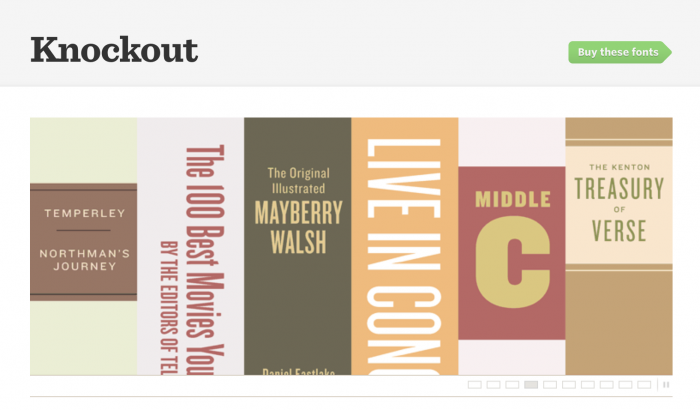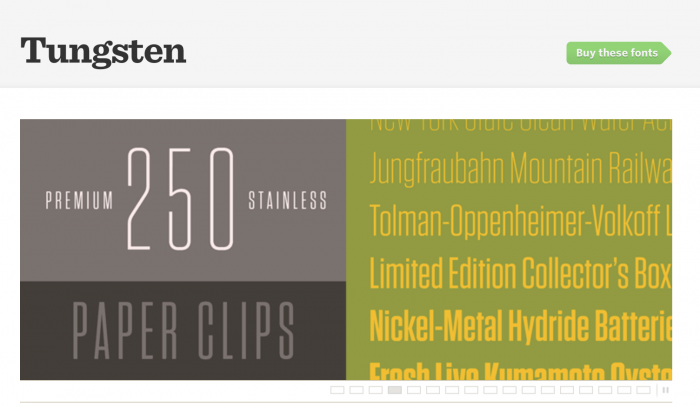
Serifenlose mit maximale X-Höhe
ich suche eine serifenlose mit möglichst großer Versalhöhe, so wie diese hier:
- ich habe das bereits Whatthefont übergeben, es war aber keine dabei.
Ich habe dann alternativ die Akzidenz Grotesk genommen, die ist aber deutlich kleiner.
Entweder ich bekomme da das falsche Bild zu sehen,  oder das ist schlicht Versalsatz.
Ich habe den OP korrigiert.
? ... ich sehe das:
und das ist eben Versalsatz, und eben keine Schrift mit großer x-Höhe - wenn du dieses Bild meinst.
Und dass das Versalsatz ist, weiß ich selbst. Deswegen steht da ja auch:
ich suche eine serifenlose mit möglichst großer Versalhöhe, so wie diese hier: (...)
Hallo Blackerl, ich vermute mal, was Du suchst ist eine serifenlose Schrift, die möglichst compressed oder condensed ist, um diesen hohen, schmalen Eindruck zu erzielen, oder? Schau Dir doch mal die Heroic condensed an, die Tungsten oder die Knockout. Und auch condensed-Schnitte ganz normaler Schriften wie Univers oder Neue Helvetica könnten sich für Deine Zwecke eignen.
Bezgl. der Schrift: Nimm doch Arial – wenn du die versal setzt und die Schriftgröße entsprechend erhöhst, hat die auch eine große Versalhöhe …  :hammer:
Auch so ist die Frage nicht besonders sinnvoll - denn ob diese Schrift eine besonders große Versalhöhe hat, sieht man erst, wenn man dann auch deren Gemeine sieht. So ist es schlicht eine halbfette Condensed-Schrift, deren Zeilenabstand für dieses Bild verringert wurde. Welcher Font das jetzt genau ist, kann ich allerdings jetzt nicht sagen
Ich habe sehr wohl erkannt, was du da meinst, dann sus deinem Bild nur den Text raus geschnitten, damit WhatTheFont oder WhaFontIs da auch die Buchstaben herauslesen kann (das ganze Bild da hochladen geht nämlich nie, esw muss immer nur der möglichst auf Schwarzweiß herunter gesetzte Teil NUR mit Schrift sein) und da geschaut, genau deine Schrift zu finden. Nachdem das nichts brachte, habe ich meine Sammlung durchsucht, wobei bei mirt Impact noch am nächsten ran kam, aber eben auch nicht 100%.
Wenn ich also hier versuche,  dir deine Begriffe klar zu machen,  ist das auch als Service gedacht, damit du bei ähnlichen Fragen eben auch leichter eine richtige Antwort bekommst, und auch, wenn dir das Quer geht:
Das 1. wäre eine Schrift mit besonders großer Versalhöhe, das 2. mit besonders großer x-Höhe.
...und dann eben auch nur wieder durch eine sachlich ebenso wenig voll zutreffende Bezeichnung (OK, schon näher dran) ersetzt, darf man da nicht sagen, was es dann wirklich ist?
Ich hatte doch nur geschrieben, dass du nach Condensed und Halbfett Ausschau halten musst. Derweil hab ich auf meinem Rechner nach dem besten Treffer gesucht, und wollte dies dann nachreichen.
Condened ist eben besonders hoch im Vergleich zur Laufweite.
Ich weiß, ich habe den Shit studiert. War ein Gehirnfurz, wenn Du so willst.
Tipp: Seinen Mitmenschen ein Mindestmaß an Intelligenz unterstellen. Alleine die Tatsache, dass mir jemand erklärt, wie in Bilder mit einem Rechtsklick abspeichere, oh mein Gott ...
Dabei gehe ich auch davon aus, dass der Strang hier von Leuten mitgelesen wird, die das nicht wissen, Wenn ich das vielleicht überkomplett schreibe, weiß ich ja nie, was genau der Fragesteller weiß und was nicht, bzw was für einen zufälligen Mitleser noch nicht klar ist
Bitte Blackerl – Catfonts hat ganz nett und sachlich versucht zu erläutern, was er gemeint hat und dass, bzw. wie er Dir helfen wollte. Ich weiß nicht ob es so ist, aber Du liest Dich ganz schön gereizt – das ist an dieser Stelle nicht wirklich zielführend. Niemand unterstellt Dir irgendetwas – ob respektierlich oder  despektierlich – sondern alle reagieren schlicht auf Deine Anfrage. In diesem Forum gibt es so viele Menschen, die sachfremd sind und Anfängerfragen stellen, dass man immer auch bereit ist, ganz am Anfang anzufangen, also zum Beispiel beim Rechtsklick – das sollte Dich also nicht kränken. Dass Du das Thema studiert hast, steht Dir nicht auf die Stirn geschrieben – Du musst es schon kommunizieren, wenn Du uns die Einordnung Deiner Kenntnisse erleichtern willst. Aufgrund Deiner Wortwahl war es vielleicht nicht im ersten Moment zu erkennen … Ansonsten gilt wie immer: Das hier ist alles freiwillig und Freizeit, jeder hilft, wenn er kann, und in der Regel gerne.  :-)